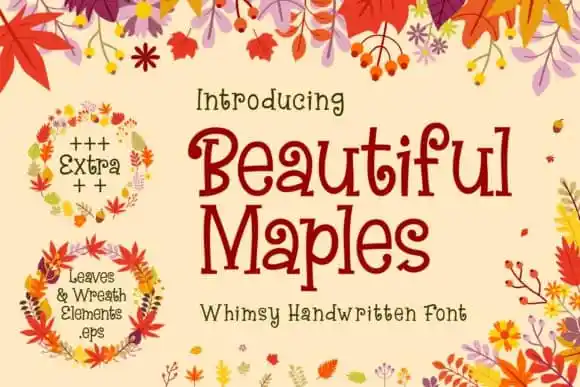
Beautiful Maples Display Font
A Beautiful Maples Display Font é uma elegante adição para designers que desejam dar um toque alegre e moderno às suas criações visuais. Esta fonte, criada pela 7NTypes e disponível no site de design 99designs, convida os artistas digitais ao permitir que seus textos ganhem uma aparência divertida, vibrante e atualizada. É perfeitamente adequada para ambientes como viagens ou marcações não-formais que buscam criar um visual atraente e inovador. A Beautiful Maples foi projetada com o objetivo de transformar qualquer idéia criativa em um elemento destacado na tela, seja ela uma embalagem, um cartaz ou até mesmo um logotipo. Seu design original, tanto em maiúsculas quanto minúsculas, a torna uma fonte versátil e multifuncional. Uma das características mais encantadoras desta fonte é sua inspiração na escrita à mão. Esta qualidade única faz com que ela se destaque em qualquer aplicação visual, oferecendo uma personalidade única e autêntica aos elementos que usa. Seja para decorar um site de moda ou criar material publicitário para viagens internacionais, a Beautiful Maples Display Font é a escolha perfeita para quem busca dar um toque especial à sua arte digital.